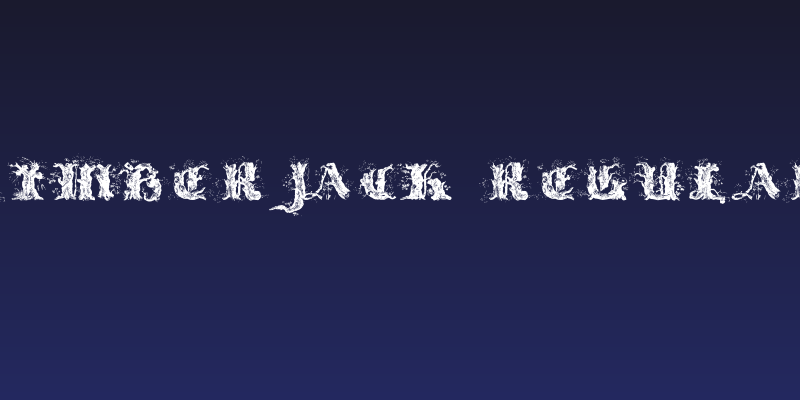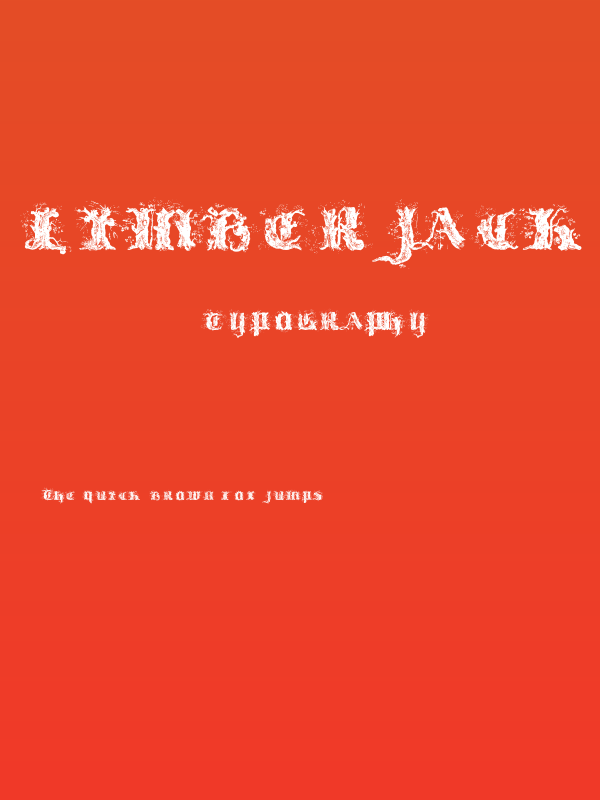
Limberjack Regular Font
✎ Gothic
| Anwendungsfall | Logos, Headlines, Posters |
| Vorgeschlagene Projekte | Ideal for album covers, posters, gothic-themed events, or any project needing a dramatic, artistic touch. |